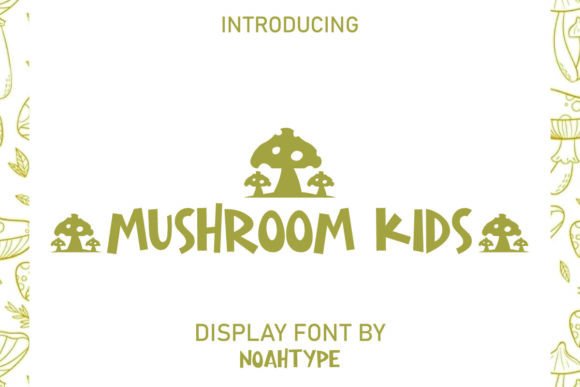
Mushroom Kids
Att hitta rätt designelement kan vara utmanande, men Mushroom Kids erbjuder en exceptionell samling som omedelbart lyfter ditt arbete.
Oavsett om du skapar POD-produkter (Print on Demand), bröllopsinbjudningar eller grafik för sociala medier, är Mushroom Kids ett perfekt val.